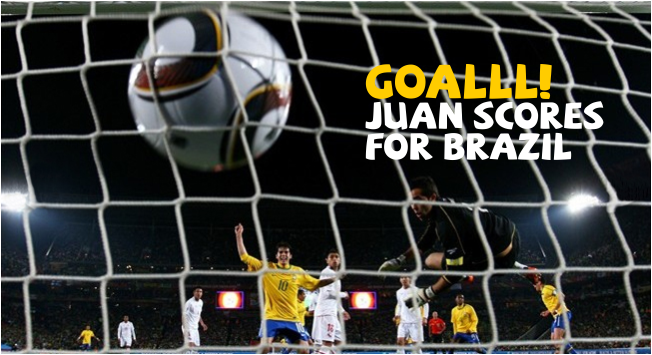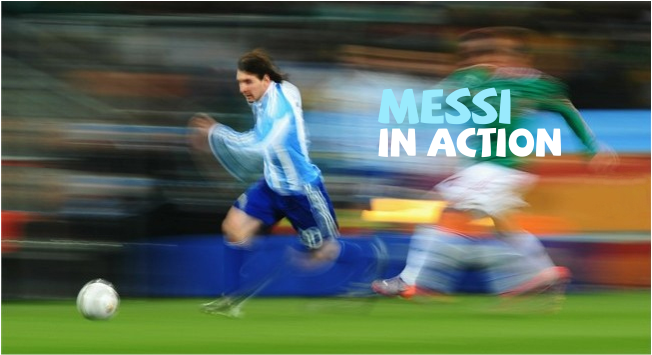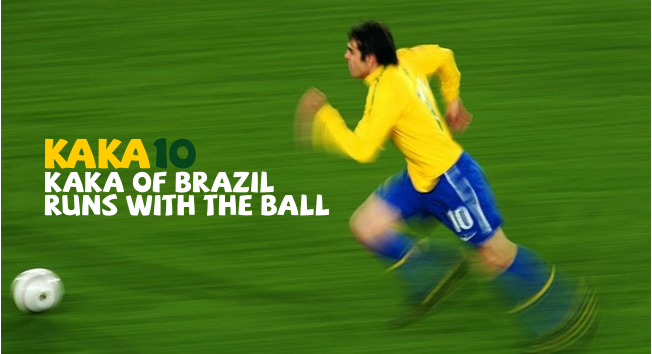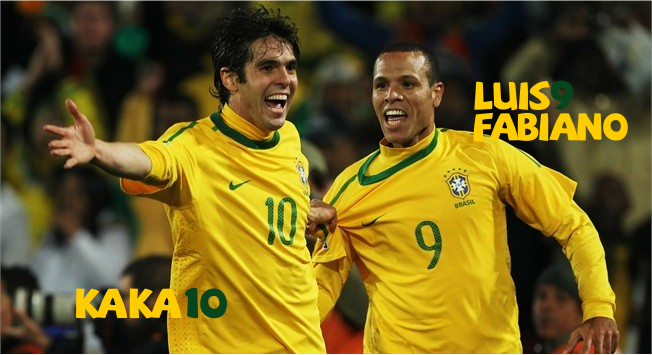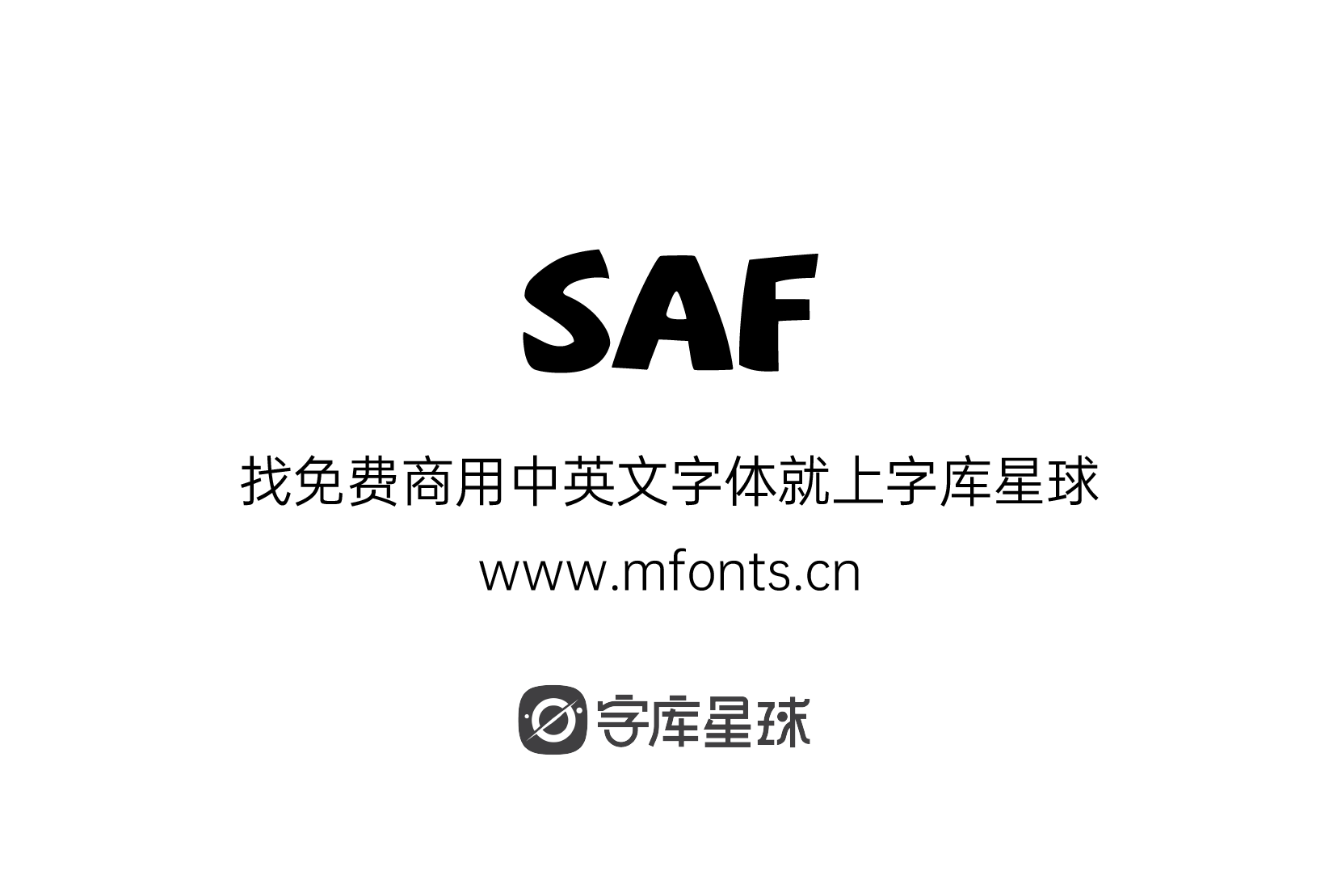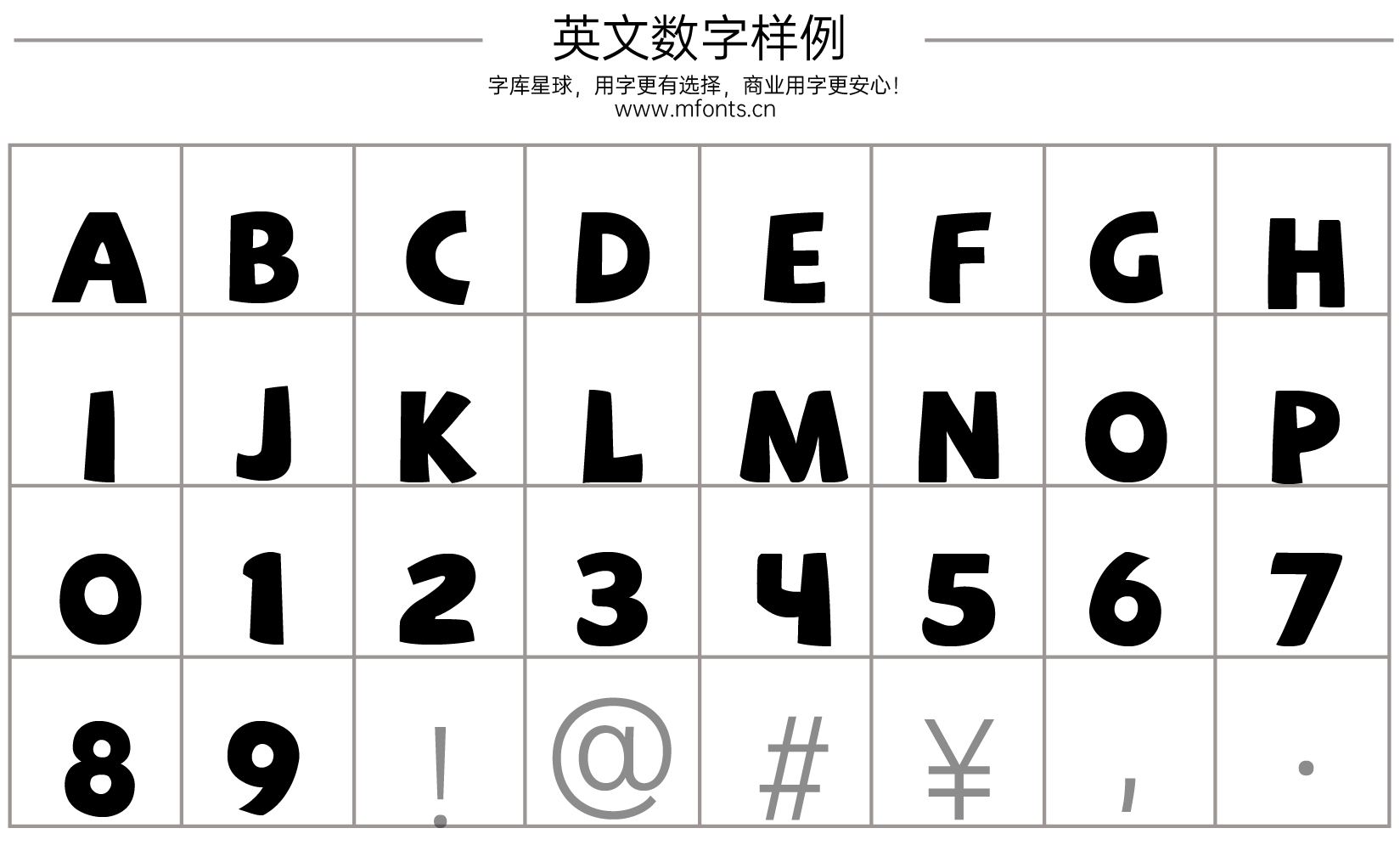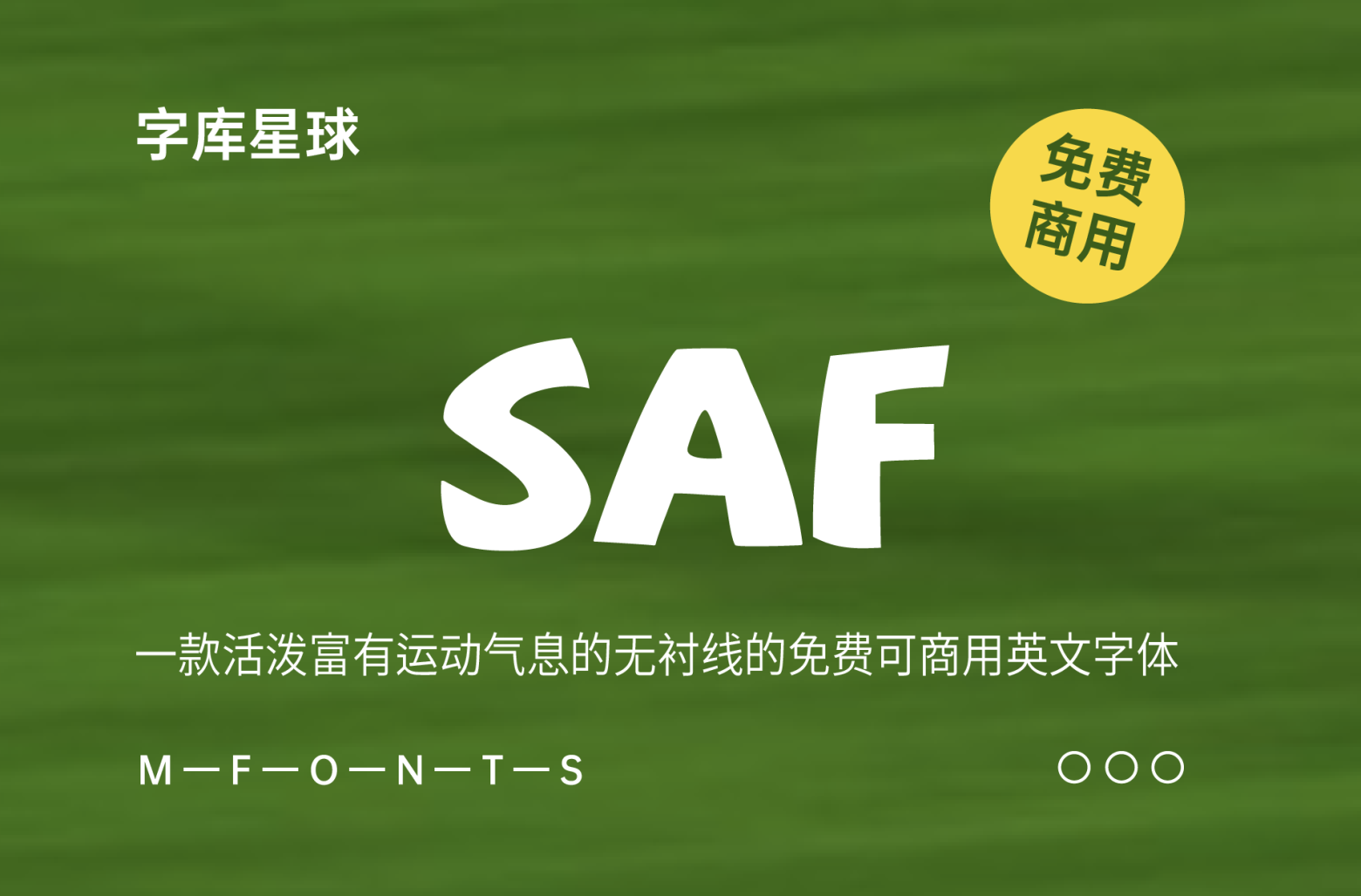
SAF
SAF免费字体的灵感来源于这种特殊的休闲字体,并加入了一些非洲的 “Ayoba”(一个南非编造的单词,意思是 “酷/凉爽”),它是一种显示字体,可在Fontfabric下载。我们并不是原始字体的作者–我们只是简单地矢量化了WC官方徽标中的一些字母和符号,并构建了无衬线字体系统的其余部分。欢迎免费下载。只有从左到右的强烈字形 + 包含中性字体。